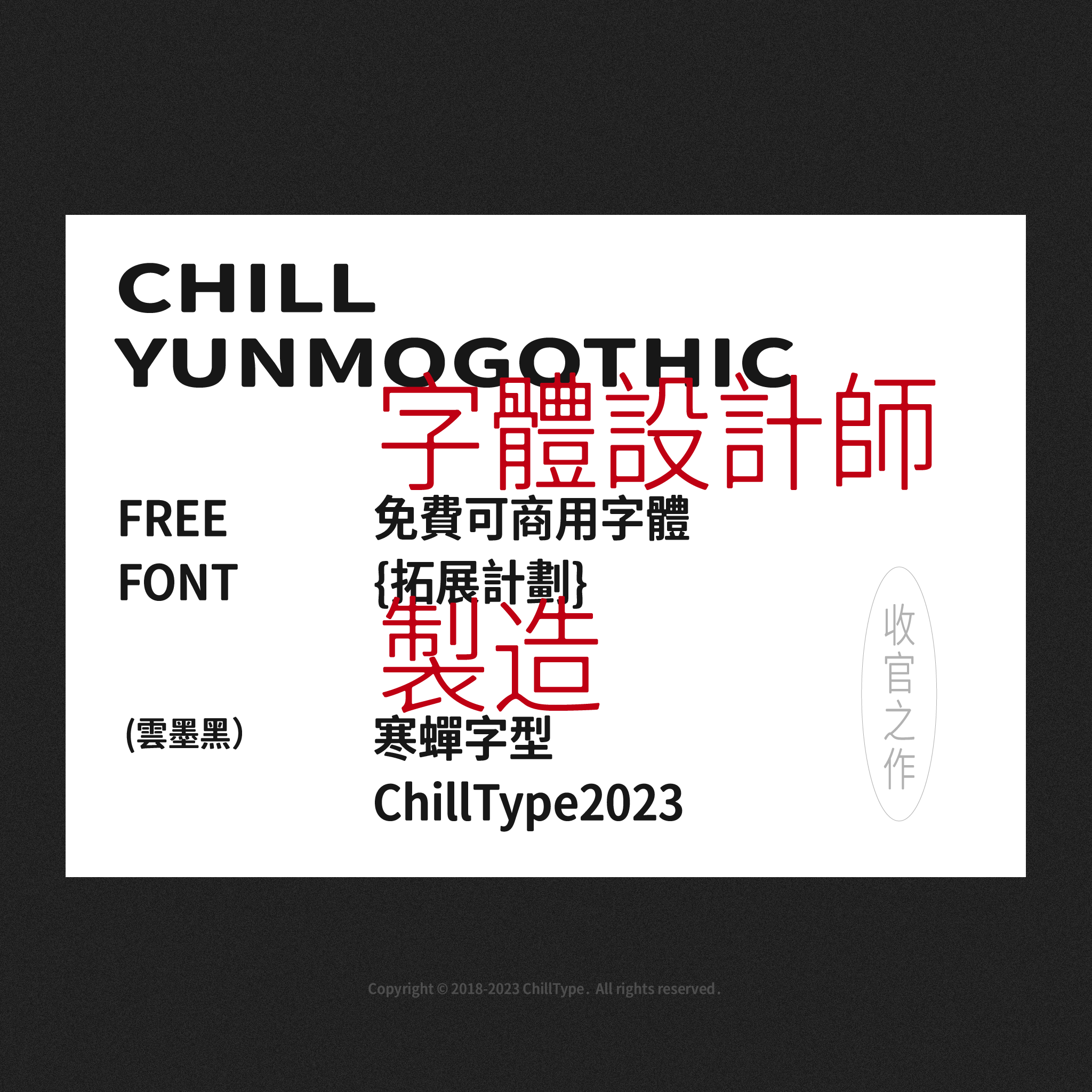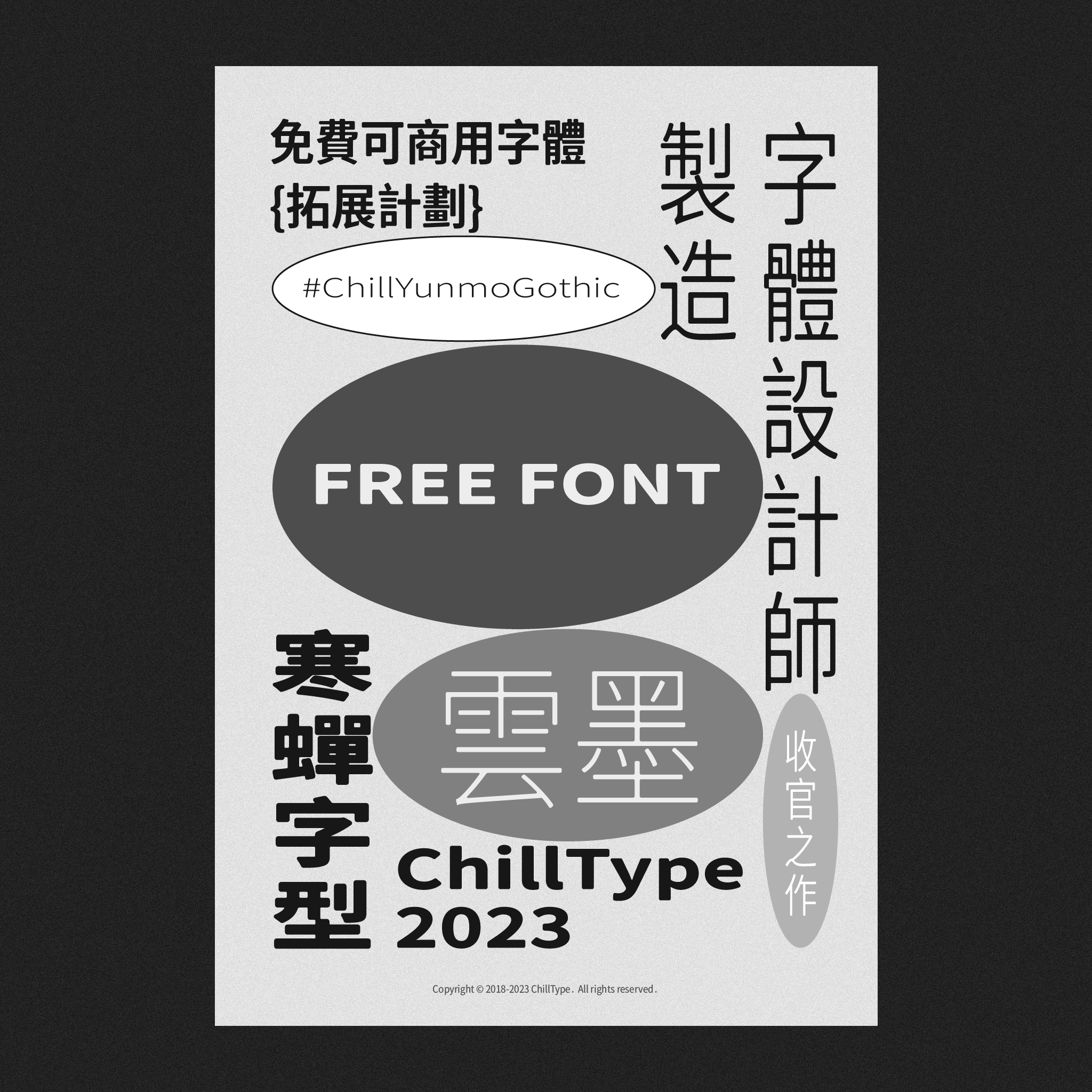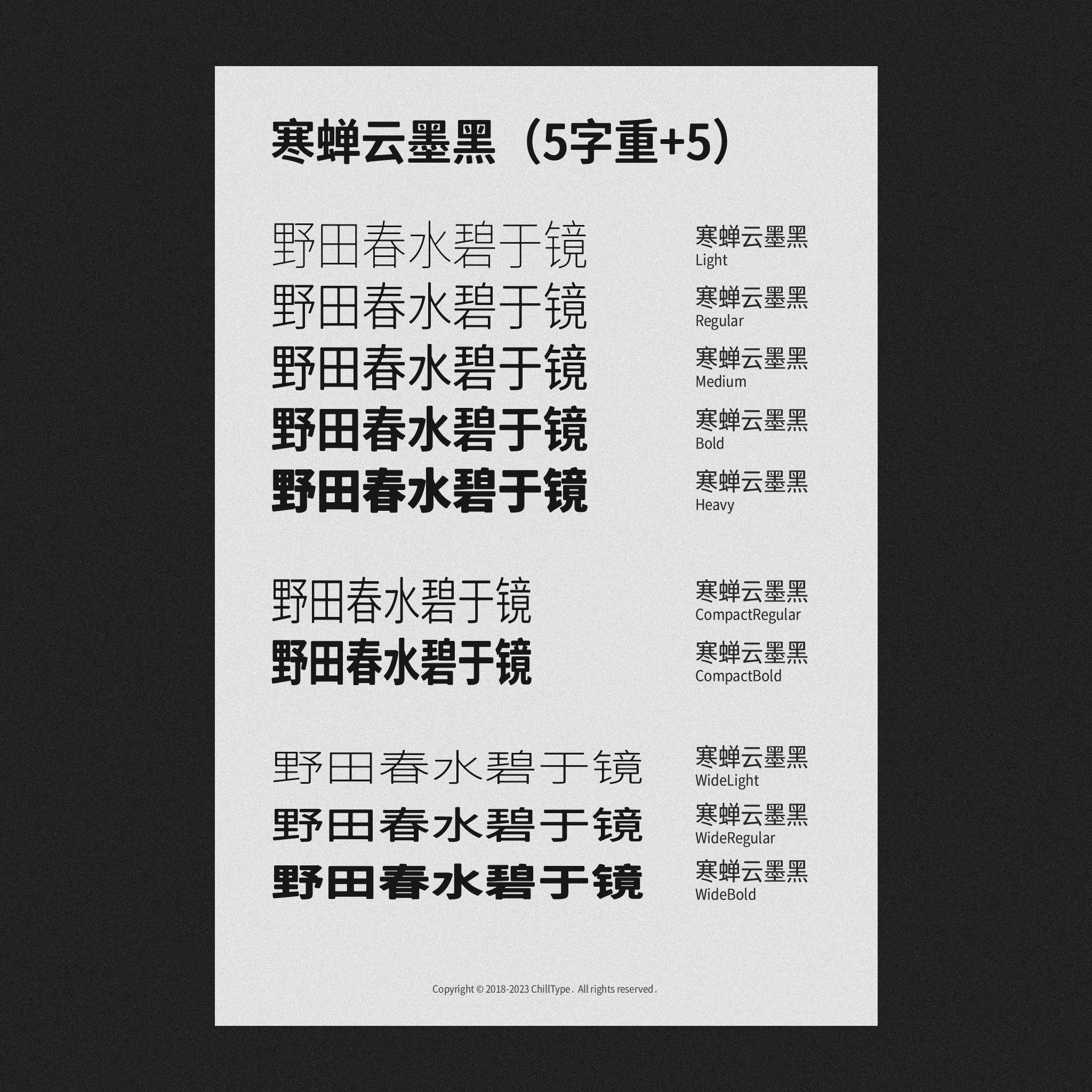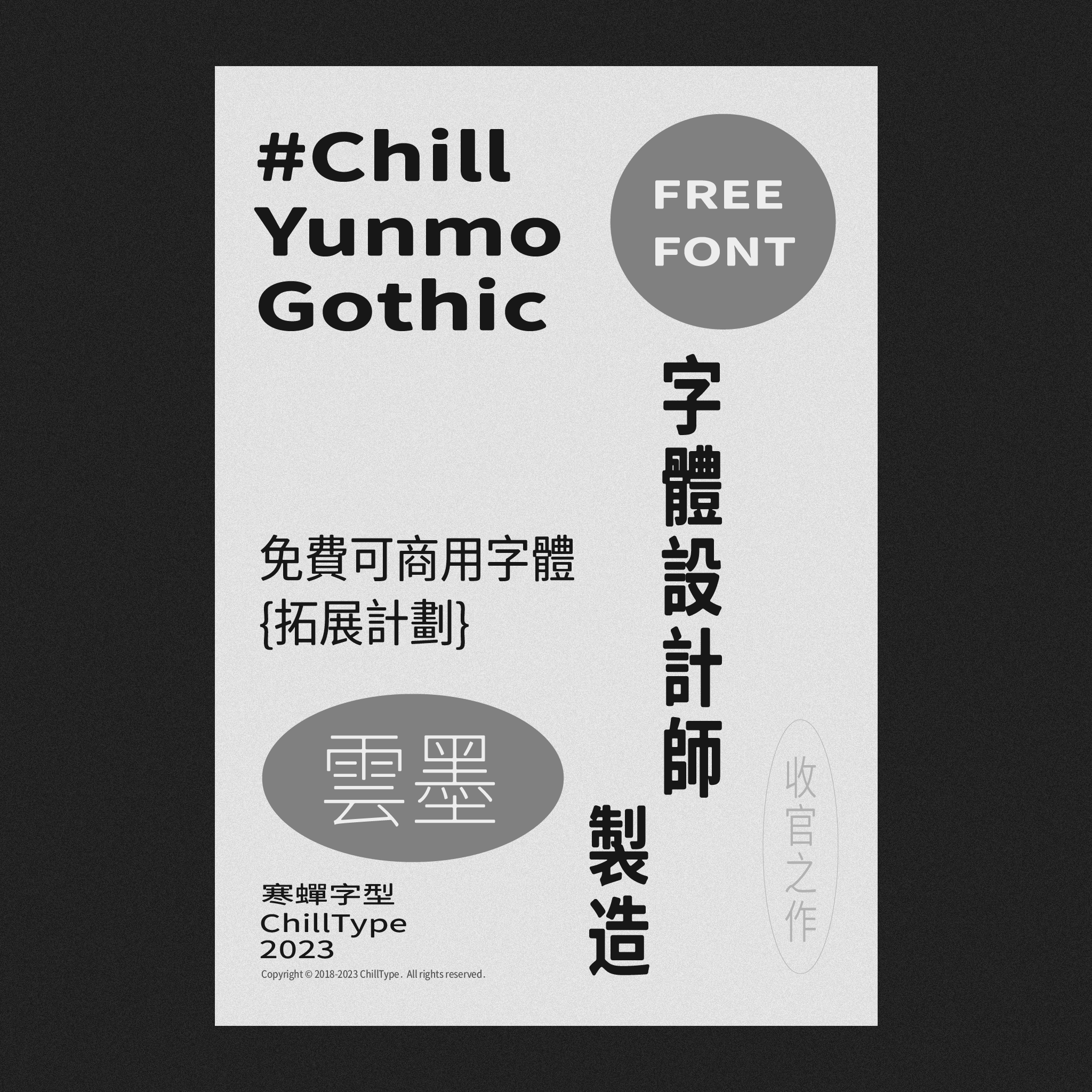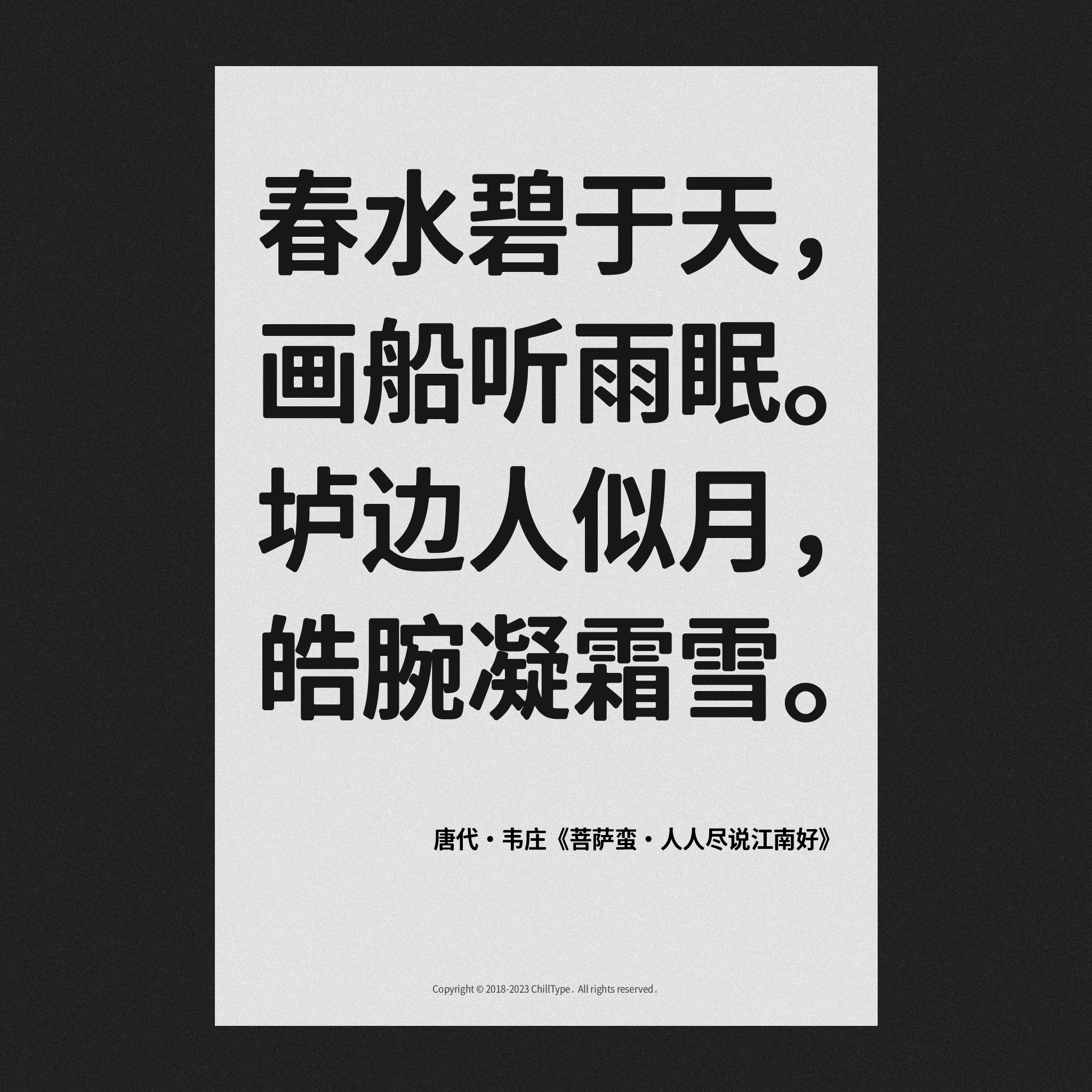
寒蝉云墨黑 是一款基于广受欢迎的思源黑体(SourceHanSansSC)进行深度修改与再创作的字体。它继承了原字体清晰易读的核心优势,并在此基础上进行了细致的优化。通过精心添加圆角处理,不仅柔化了字体边缘的生硬感,还赋予了它更加温润、亲和的视觉特质,使其在各类设计场景中都能传递出温暖而不失现代感的气质,特别适用于需要营造亲切氛围的界面或品牌标识。 在排版细节方面,这款字体经过全面优化,涵盖字间距、行距以及字符对齐等关键元素。通过微调这些细节,有效提升了文本的可读性和整体美感,使得长段落阅读更加舒适,图文混排也更为和谐统一。同时,对字体的字重比例进行了重构,确保从细体到粗体的过渡更加平滑协调,增强了字体的层次感和适应性。无论是用于屏幕显示的UI设计,还是印刷媒介的排版应用,寒蝉云墨黑都能表现出色,满足多样化的视觉传达需求。